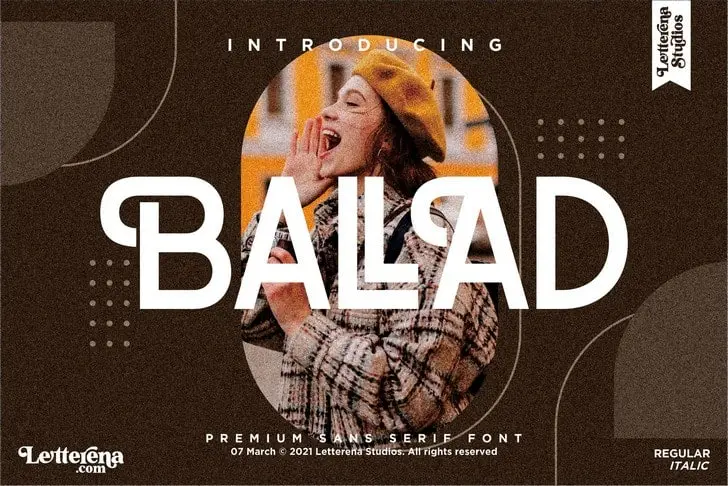
Ballad Sans Serif Font – Download Grátis
A Ballad Sans Serif Font é uma elegante tipografia sans-serif que incorpora a funcionalidade OpenType para tornar seus designs mais sofisticados e luxuosos. Perfeita para um vasto leque de projetos, desde identidades visuais até materiais promocionais como mugs, cartões de visita e convites, esta fonte abraça uma variedade de usos que valorizam sua natureza moderna e requintada. Seja ele o design de logomarcas para marcas renomados ou a criação de embalagens sofisticadas para produtos gourmet, a Ballad Sans Serif é a escolha perfeita para quem busca arquitetar um projeto com uma personalidade única e um toque de classe. Ela traz a beleza minimalista da tipografia sans-serif em harmonia com as nuances luxuosas que você precisa para levar suas ideias ao topo.